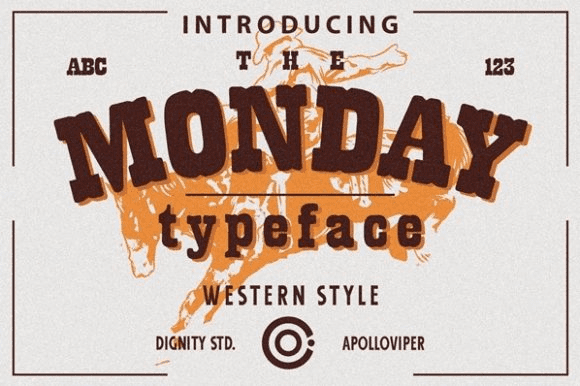
[Creativefabrica] Monday Font
Название: Monday Font
[Creativefabrica] Monday Font
Понедельник - это жирный, западный шрифт.
Используете ли вы его для дизайна мультфильмов, детских игр, цитат, названий, фирменных наименований, обложек книг, плакатов, или просто для любого творения, требующего прикосновения красоты, этот шрифт - отличный выбор.